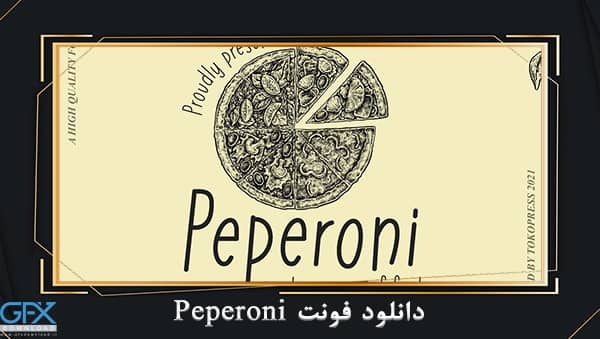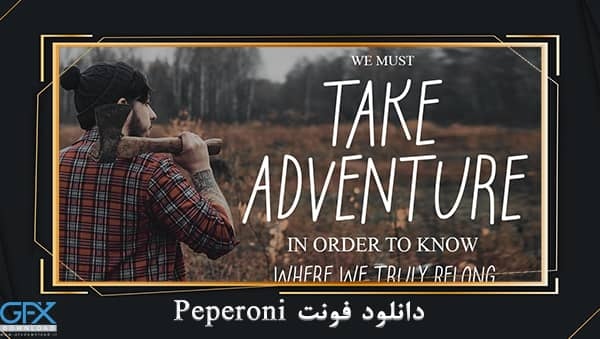
دانلود فونت پپرونی Peperoni
فونت زیبای پپرونی دست نویس
دانلود فونت زیبای پپرونی دست نویس Peperoni
این فونت بسیار جذاب و دست نویس زیبایی و محیط آرامش بخشی را برای مخاطب به ارمغان می آورد. دانلود فونت پپرونی Peperoni مناسب برای مجله های دسته بندی شده زنانه ، پوستر ، عنوان فیلم ، پوستر موسیقی ، جلد های یوتیوب ، تصاویر کوچک یوتیوب ، جلد صفحات رسانه های اجتماعی و غیره می باشد. با طراحی شاد . شما می توانید برای چاپ و صفحه نمایش از این فونت استفاده نمایید